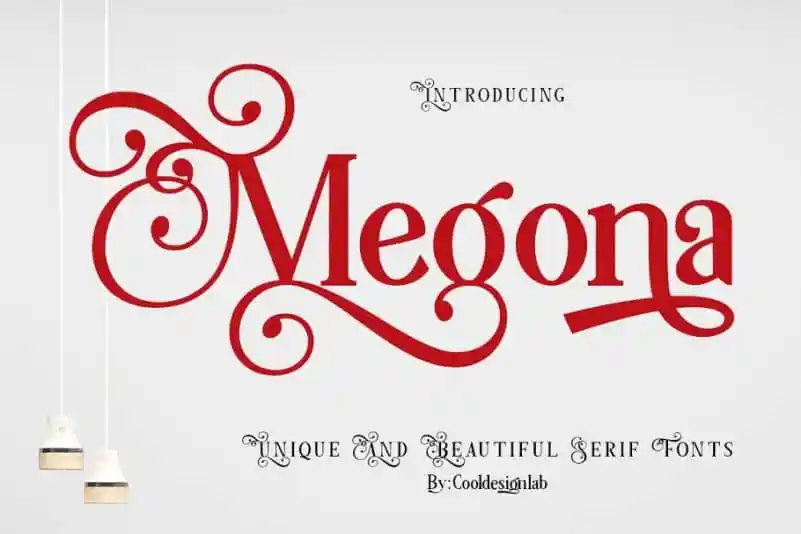
A fonte “Megona Serif” é uma escolha elegante para qualquer projeto que deseje destacar-se. Com seu peso forte e formas arredondadas, essa fonte garante leitura clara tanto para cabeçalhos quanto para texto completo. Ela traz um toque de luxo e sofisticação ao design de sua apresentação ou material impresso. O fato de suportar múltiplas línguas e o uso do PUA (Portuguese Unicode Area) permitirá que você personalize ainda mais seu layout, garantindo uma identidade visual única e chamativa. Esta fonte é perfeita para quem busca um toque diferenciado em seus projetos, seja para um site elegante, uma impressão profissional ou até mesmo para o design de material gráfico criativo.